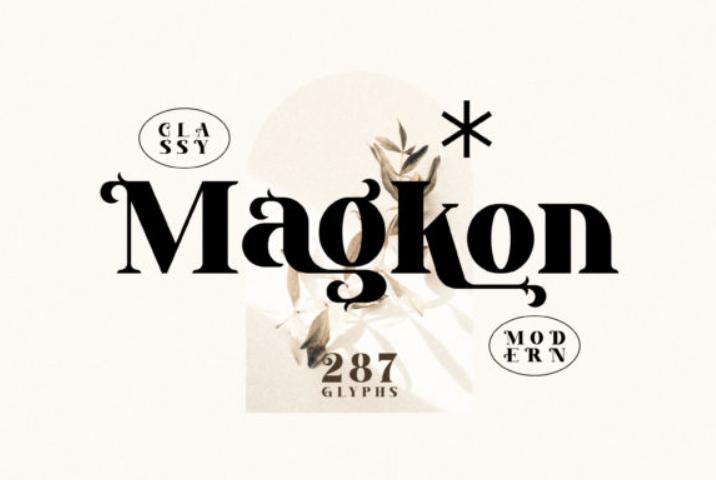
Magkon - это стильный, жирный и элегантный шрифт с засечками. Этот универсальный скриптовый шрифт имеет широкий спектр применений, от поздравительных открыток до заголовков, и гарантированно добавит особой атмосферы вашему следующему проекту. Magkon имеет кодировку...